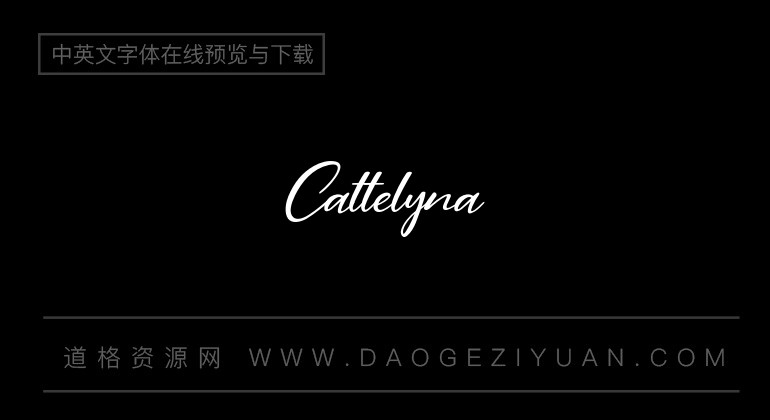
? Cattelyna 字体是一款拥有明亮的色彩和轻松的外观的可爱温暖的花式字体。它有一种温柔优雅的节奏,可以给您的设计带来温暖的感觉。它是一款多功能字体,可以用于各种设计,包括卡片,海报,商标,书籍封面,显示和网页设计等等。它的线条细腻,曲线优美,可以提供出色的文本和标题,使您的设计更加出色。内容介绍
Cattelyna是一款非常不错的手写艺术字体,具有很好的视觉感,适合于文化类的宣传设计、商业类品牌的广告和产品包装设计以及个性化文字排版等较多场景。